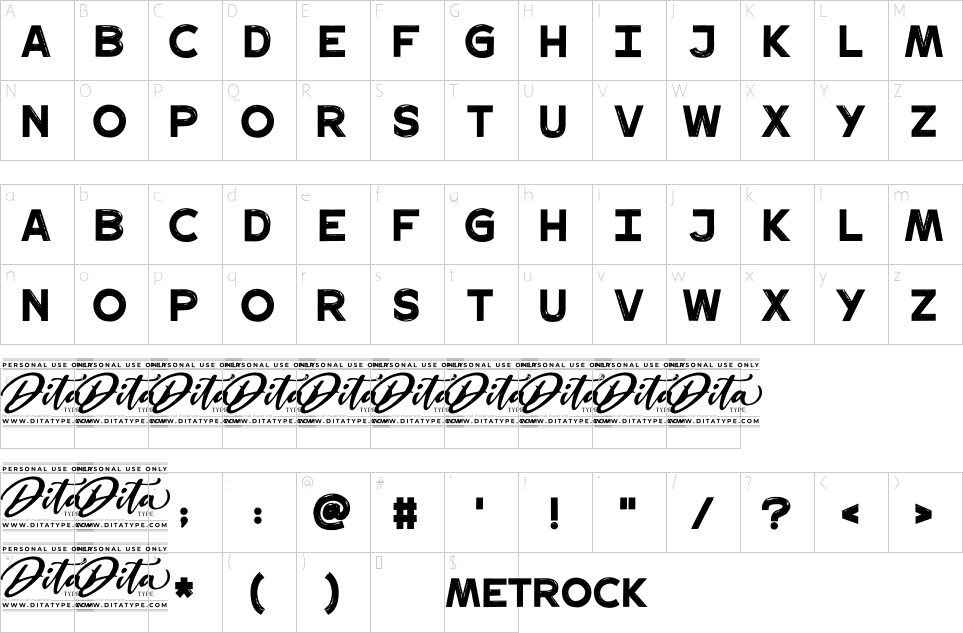
A fonte Metrock é uma opção gratuita e fácil de usar para estilos gráficos diversos. Desenvolvida pela Dita Type, essa fonte vem com 1001 opções de download, tanto para sistemas Windows quanto Mac. Com uma estrutura levemente romanesca, a Metrock é ideal para criar uma variedade de efeitos e texturas em projetos digitais. Seja para o design de sites, criação de logotipos ou até mesmo para decorar textos em documentos, Metrock oferece um conjunto de recursos únicos que vão muito além da simples escrita. Com seus 1,630 downloads, é uma fonte que tem se destacado em diversos ambientes, tanto profissionais quanto de design pessoal. Se você está procurando uma fonte que seja de fácil acesso e com um desempenho impressionante, Metrock é o tipo de fonte que você provavelmente vai querer incluir em sua coleção.